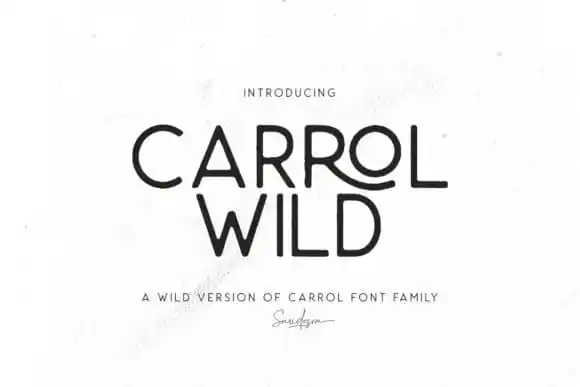
Carrol Wild Sans Serif Font – Fonte Grátis
Carrol Wild Sans Serif Font
A Carrol Wild Sans Serif Font é uma elegante tipografia sem serif criada por saridezra com alegria de modernidade e simplicidade. Seu estilo único e autêntico pode inspirar você, permitindo que crie cartões de apresentação encantadores, arte de papel higiene impecável, pôsteres capturantes para redes sociais e cartas de cumprimento adoráveis. Ideal tanto para eventos como festivais de casamento quanto para criação de conteúdo pessoal online. Este é um recurso gráfico que certamente enriquecerá suas propostas digitais e impressas.